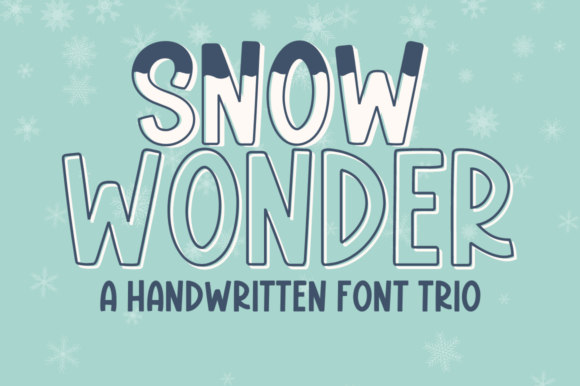
Snow Wonder Trio
Jika anda sedang mencari aset berkualiti tinggi seperti Snow Wonder Trio, pakej premium ini merupakan pilihan yang hebat untuk projek kreatif anda.
Sama ada anda mencipta produk POD (Print on Demand), jemputan perkahwinan atau grafik media sosial, Snow Wonder Trio amat bersesuaian.